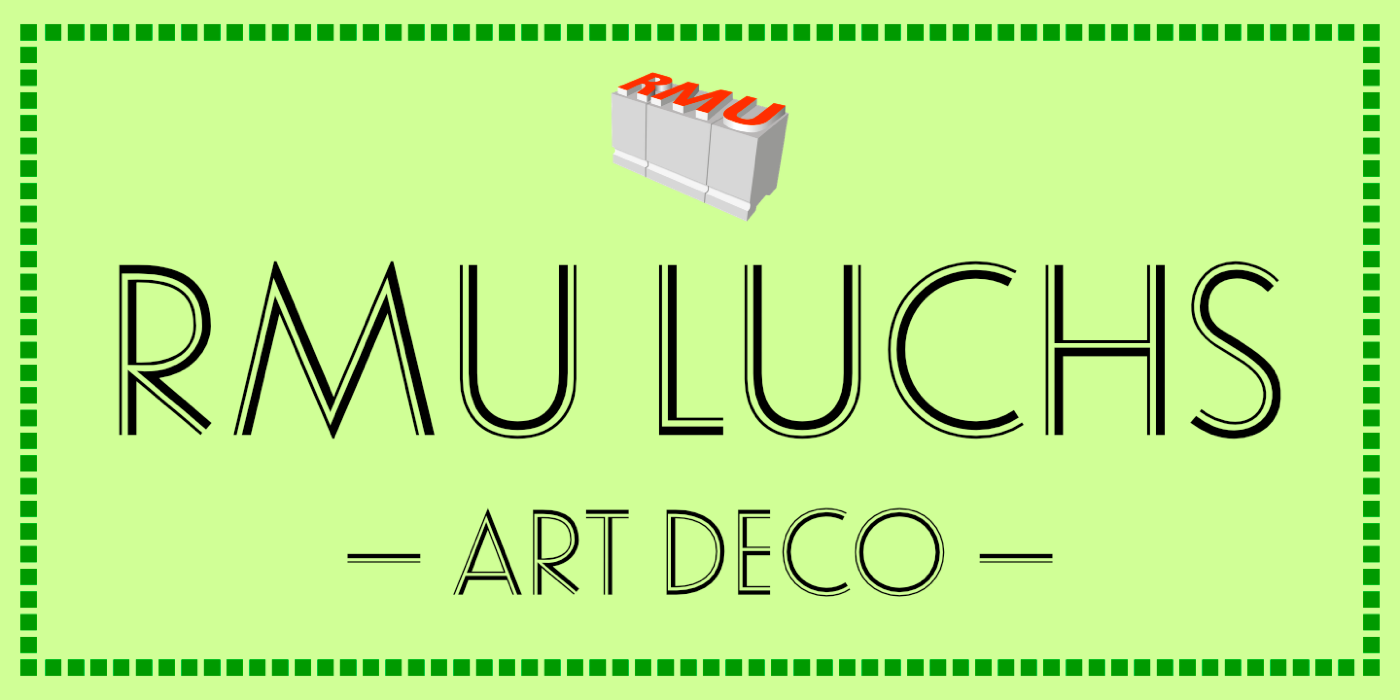
• 1929
• Antiqua dekorativ
Die Lux ist ein lichtes Versalalphabet, das von der Erbar-Grotesk abgeleitet wurde. Die Schrift erschien Ende der 1920er-Jahre bei Ludwig & Mayer.
Eine Digitalisierung mit erweiterter lateinischer Belegung gibt es als RMU Luchs von RMU Fonts.